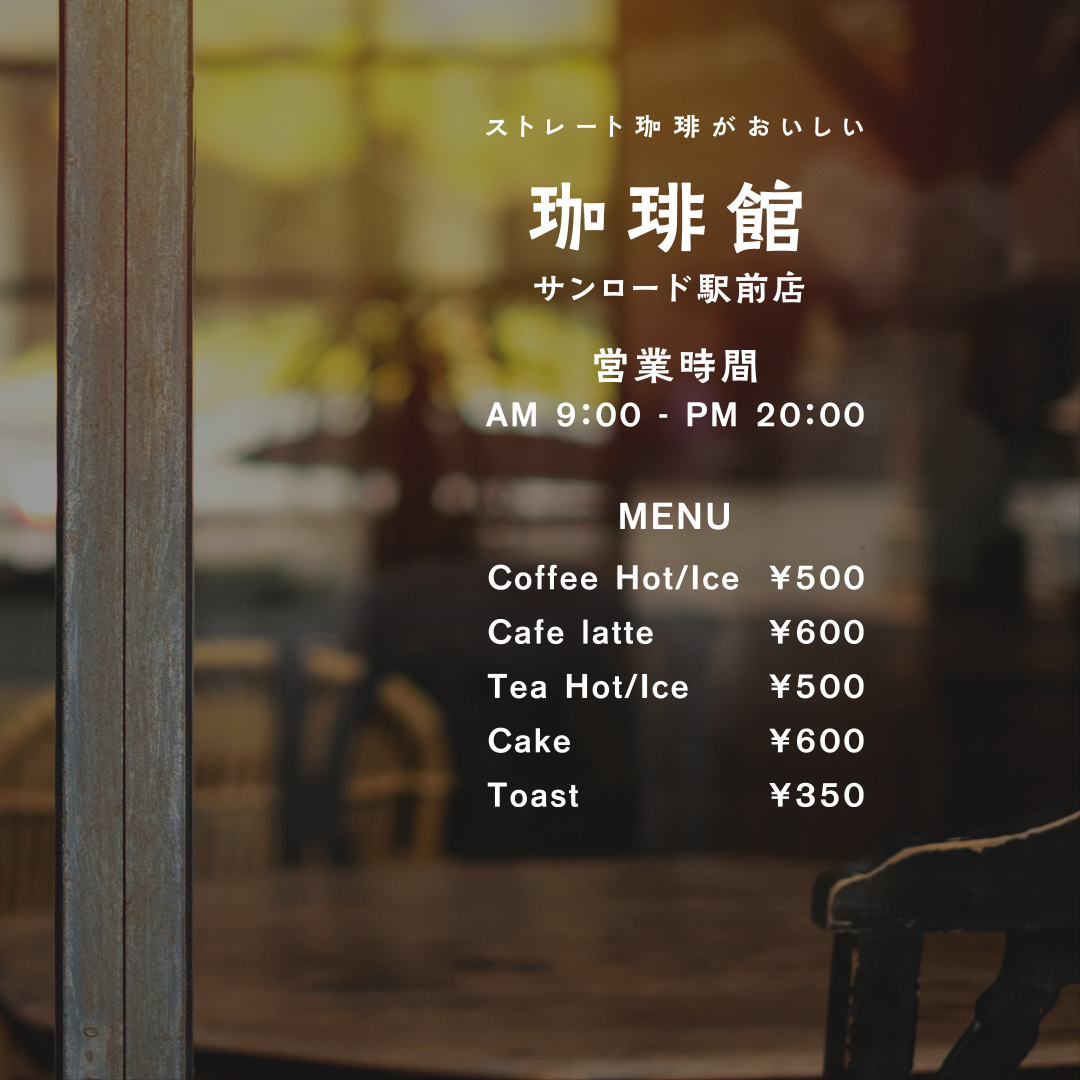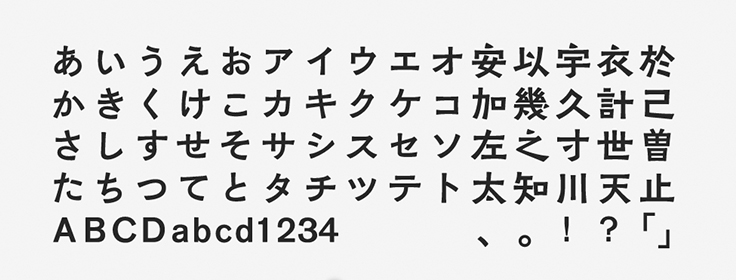
「くれたけ銘石」について
くれたけ銘石は、漢字書体の銘石と、和字(かな)書体のくれたけを組み合わせたゴシック体として2020年に登場しました。銘石は中国南京市の郊外で出土した晋代の墓誌銘「王興之墓誌」から復刻した漢字書体です。くれたけは森川龍文堂の活字見本帖「活版総覧」から復刻されています。
「くれたけ銘石」の特徴
隷書体をベースとしながら彫刻の味わいが加わった書風が特徴です。手書きの味を残したオールドスタイルのゴシック体であるため、ノスタルジックな雰囲気と素朴な魅力を備えています。
漢字では点のエレメントが三角形に近い形になっているなど、非常に独特なデザインです。和字(かな)は全体的にはすっきりと読みやすい印象ではありながら、癖の強い形の文字も多く見られます。独特な個性を放つフォントの1つです。
特に漢字のデザインが気に入っています。手作り感や無骨な印象もありますね。クラフト感のあるイメージで、使いこなしたいなと思わせる魅力的なフォントです。ちょっとした本文組みなどに使っても面白い印象に仕上がるのではないかと思います。